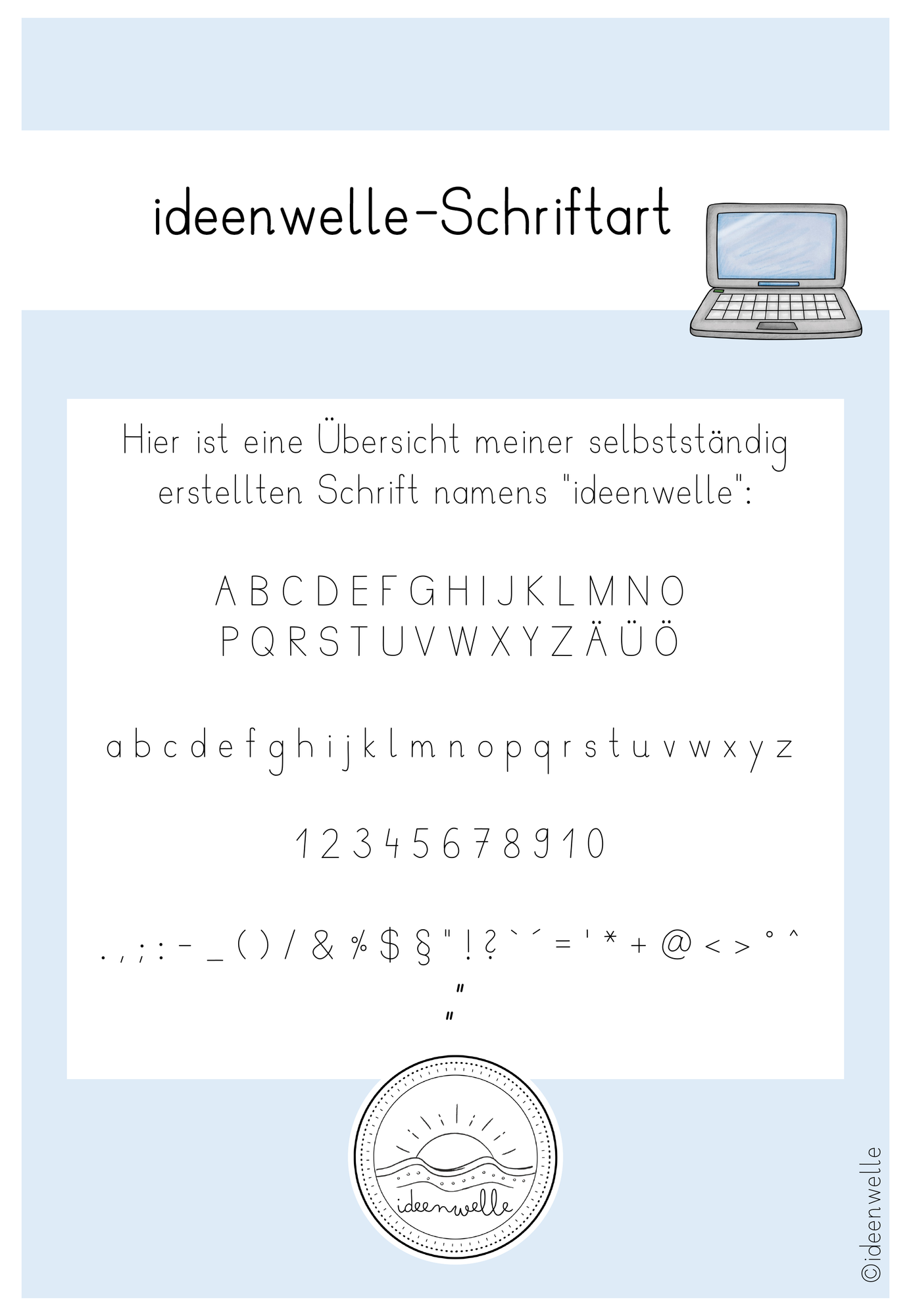
„ideenwelle“, welche ich mit dem Programm iFontMaker erstellt habe.
So eine wunderschöne und gut lesbare Schriftart findet man selten. Könntest du dir vielleicht vorstellen, ein Zusatzset mit den französischen und spanischen Buchstaben und Satzzeichen zu erstellen? Darüber würde ich mich riesig freuen.
Ich bin absolut wählerisch, was Schriftarten für mein Material angeht. Eine Schrift muss gut lesbar sein, eine für den Unterricht angemessene Darstellung haben und gleichzeitig ästhetisch angenehm aussehen.
Diese Schrift erfüllt alle Punkte und es macht mich richtig glücklich, Material damit zu erstellen. :)
Die Schrift ist toll, vor allem gut lesbar und an den Materialien orientiert, die im Unterricht zum Einsatz kommen. War schnell installiert und direkt einsatzbereit, bin begeistert!
Ich habe das Material hauptsächlich für Aushänge im Klassenzimmer benutzt und finde es total gelungen. Ich freue mich schon sehr sie für Arbeitsblätter zu verwenden.
Die Schriftart ist wirklich super!
Ich habe lange überlegt selbst eine Schriftart zu erstellen, aber hier die ist einfach top und für alle Klassen einsetzbar!
Das Material ist hervorragend, damit die Kinder die Schrift auch einwandfrei lesen können 😊 ich werde die Schrift nun wahrscheinlich auf nahezu jedem Material verwenden :)
Hi! Erstmal: Danke :) Finde die Schrift sehr gelungen! Kleiner Anmerkung: Beim "u" ist unten noch ein kleiner Schwung dran wie bei der Grundschrift. Und noch eine Frage: Werdet ihr die Schrift auch noch "fett" zur Verfügung stellen? Wenn man das über die Programme selbst macht (z.B. im WSC), dann werden die Buchstabenformen ungenau und hakelig. LG
Hey, beim kleinen u soll tatsächlich unten ein kleiner Haken zu sehen sein. So ist es auch im Flex- und Flora, welches wir in der Schule verwenden. Aber vielleicht lässt es sich bei Gelegenheit ja mal einrichten, eine weitere Schrift ohne Haken zu erstellen. Geht es da nur um das u, oder auch um weitere Buchstaben?
Wunderschöne Schriftart!
So eine wunderschöne und gut lesbare Schriftart findet man selten. Könntest du dir vielleicht vorstellen, ein Zusatzset mit den französischen und spanischen Buchstaben und Satzzeichen zu erstellen? Darüber würde ich mich riesig freuen. Lieben Dank fürs Erstellen dieser tollen Schrift ♡
Endlich die perfekte Schrift gefunden
Ich bin absolut wählerisch, was Schriftarten für mein Material angeht. Eine Schrift muss gut lesbar sein, eine für den Unterricht angemessene Darstellung haben und gleichzeitig ästhetisch angenehm aussehen. Diese Schrift erfüllt alle Punkte und es macht mich richtig glücklich, Material damit zu erstellen. :) Vielen Dank!
direkt einsetzbar
Tolle Schrift!
Die Schrift ist toll, vor allem gut lesbar und an den Materialien orientiert, die im Unterricht zum Einsatz kommen. War schnell installiert und direkt einsatzbereit, bin begeistert!
Toll!
Die Schriftarten sind wirklich toll und soo schön und perfekt für die Grundschule geeignet!😍
Schöne und leicht lesbare Schrift
Ich habe das Material hauptsächlich für Aushänge im Klassenzimmer benutzt und finde es total gelungen. Ich freue mich schon sehr sie für Arbeitsblätter zu verwenden.
Begeistert
Tolle und gut lesliche Schrift zum erstellen von Arbeitsmaterial!
Tolle Schriftart
Diese Schriftart ist für alle Klassen einsetzbar. Das Lesen ist durch diese Schrift kein Problem mehr.
Für alle Klassen top
Die Schriftart ist wirklich super! Ich habe lange überlegt selbst eine Schriftart zu erstellen, aber hier die ist einfach top und für alle Klassen einsetzbar!
Sehr hilfreiche Schrift!
Das Material ist hervorragend, damit die Kinder die Schrift auch einwandfrei lesen können 😊 ich werde die Schrift nun wahrscheinlich auf nahezu jedem Material verwenden :)